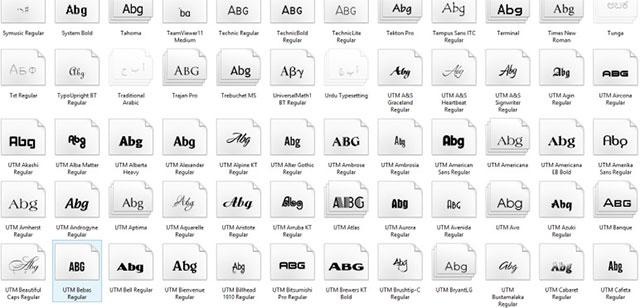
Bộ font UTM, viết tắt của Unicode Thiên Minh, là một bộ font chữ tiếng Việt phong phú và đa dạng, được thiết kế để đáp ứng nhu cầu sử dụng đa dạng của người dùng. Với 196 font UTM và 307 font SFU đã được Việt hóa, bộ font này hỗ trợ đầy đủ bộ mã Unicode chuẩn, tương thích hoàn toàn với các phần mềm gõ tiếng Việt phổ biến như Unikey hay Vietkey. Điều này đảm bảo người dùng có thể thoải mái sử dụng bộ font này mà không gặp bất kỳ vấn đề về hiển thị hay mã hóa ký tự.
Sự đa dạng và chất lượng của Bộ font UTM:
Không chỉ cung cấp các font chữ chuẩn cho việc gõ tiếng Việt, Bộ font UTM còn nổi bật với sự đa dạng về kiểu chữ, bao gồm nhiều mẫu chữ đặc sắc, mang tính nghệ thuật cao. Những font chữ này không chỉ đáp ứng nhu cầu sử dụng hàng ngày mà còn rất phù hợp cho các công việc thiết kế đồ họa, tạo ra các ấn phẩm đẹp mắt và chuyên nghiệp. Từ việc tạo banner quảng cáo, poster phim ảnh cho đến thiết kế chữ trang trí, Bộ font UTM đều mang lại những lựa chọn phong phú và đáp ứng được yêu cầu về tính thẩm mỹ cao. Sự kết hợp giữa các nét thanh, nét đậm trong bộ font cũng tạo nên sự linh hoạt, giúp người dùng dễ dàng lựa chọn font chữ phù hợp với từng mục đích sử dụng cụ thể.
Vai trò quan trọng của Bộ font UTM trong thời đại số:
Trong thời đại bùng nổ Internet và sự phát triển mạnh mẽ của các công cụ giao tiếp trực tuyến, nhu cầu sử dụng font chữ tiếng Việt chuẩn xác và đa dạng càng trở nên cấp thiết. Các ứng dụng chat phổ biến như Zalo, Skype, Viber hay Halo đều tích hợp các font chữ hệ thống. Việc cài đặt đầy đủ các font chữ này giúp đảm bảo quá trình giao tiếp diễn ra suôn sẻ, người dùng có thể dễ dàng đọc và hiểu nội dung tin nhắn, đồng thời thể hiện được cá tính và phong cách riêng trong quá trình trò chuyện. Bộ font UTM đóng vai trò quan trọng trong việc bổ sung đầy đủ các font chữ cần thiết, giúp người dùng khắc phục tình trạng thiếu font chữ và đảm bảo khả năng hiển thị tiếng Việt một cách chính xác trên các nền tảng trực tuyến.
Kết luận:
Bộ font UTM là một lựa chọn tuyệt vời cho những ai cần một bộ font chữ tiếng Việt đa dạng, chất lượng cao và hoàn toàn miễn phí. Với sự đa dạng về kiểu chữ, khả năng tương thích cao và quá trình cài đặt đơn giản, Bộ font UTM chắc chắn sẽ đáp ứng được nhu cầu sử dụng của đa số người dùng. Việc bổ sung Bộ font UTM vào hệ thống máy tính sẽ giúp người dùng có trải nghiệm gõ tiếng Việt tốt hơn, làm phong phú thêm lựa chọn font chữ và tăng tính thẩm mỹ cho các sản phẩm thiết kế. Sự tiện lợi, chất lượng và tính miễn phí của bộ font này chính là những yếu tố tạo nên sức hút và giá trị của Bộ font UTM.